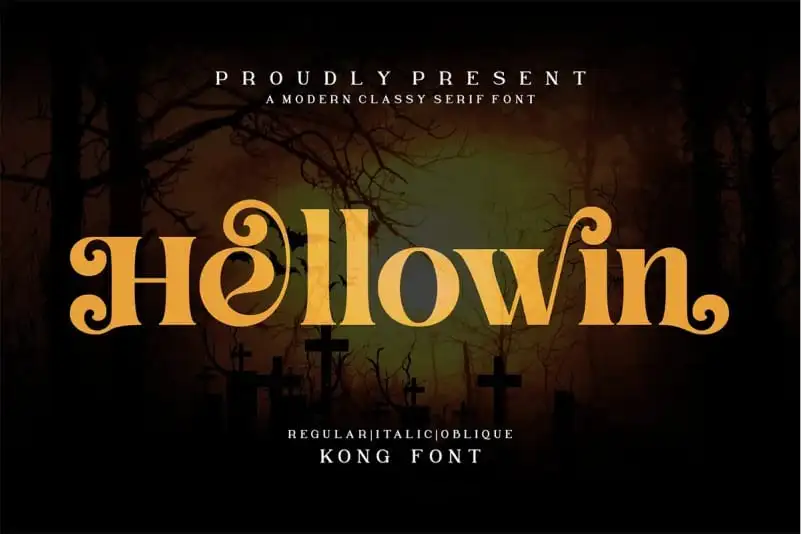
Hellowin Serif Font – Download Grátis
A Hellowin Serif Font é uma tipografia sans serif com um visual retro, criada especialmente para ambientes de design que valorizam sofisticação e elegância. Esta fonte apresenta mais de 100 ligaturas, capas menores e swashes, proporcionando uma versatilidade impressionante em diferentes tipos de projetos. Ideal para criações de logo luxuoso ou marca, designs estilizados para revistas e moda, embalagens de boutique, design de material de escritório, blogs modernos, propaganda publicitária de alta qualidade, cartas de convite e até mesmo decoração em casa. A Hellowin Serif Font também oferece uma paleta perfeita para títulos de livros ou capas, bem como qualquer evento especial que desejamos destacar. Com sua simplicidade moderna e aparência retrô, ela é um recurso indispensável para todos aqueles que buscam criar designs impecáveis.